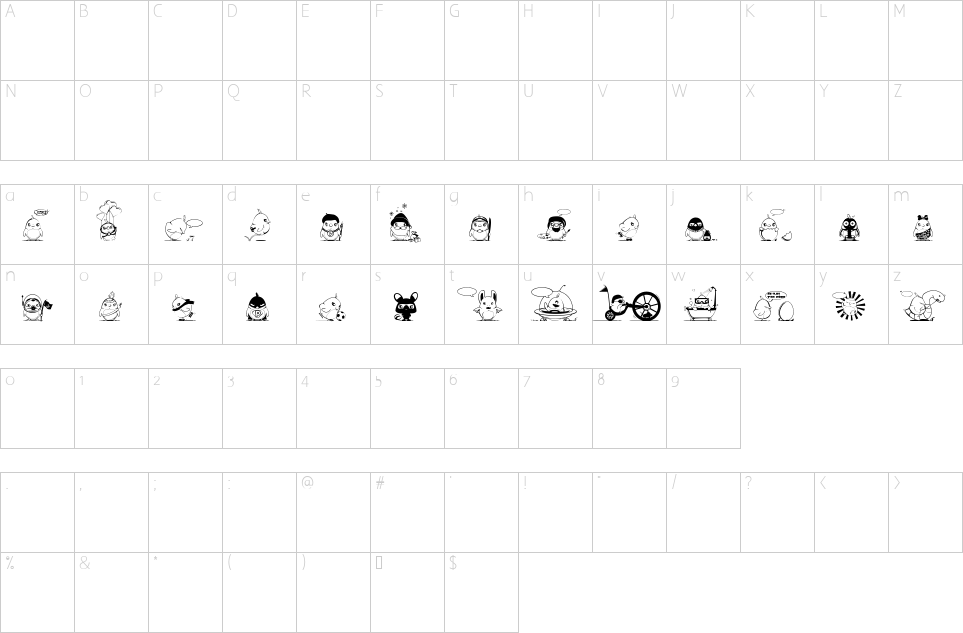
A fonte Piou é um presente gratuitamente disponível para download para Windows e Mac, criada por Maelle Keita. Com um design minimalista e elegante, a Piou é perfeita para designers de sites, designers de logotipos e qualquer um que procura uma fonte de qualidade para adicionar um toque único a seu projeto. Com 2,934 downloads ao longo de seu lançamento, a fonte Piou provavelmente atingiu um grande número de usuários apaixonados. Essa fonte é uma ótima escolha para aqueles que buscam uma opção livre de custos, ainda assim mantendo um padrão de qualidade de design. Agrade-se à fonte Piou para contribuir para o seu design e estilo único.